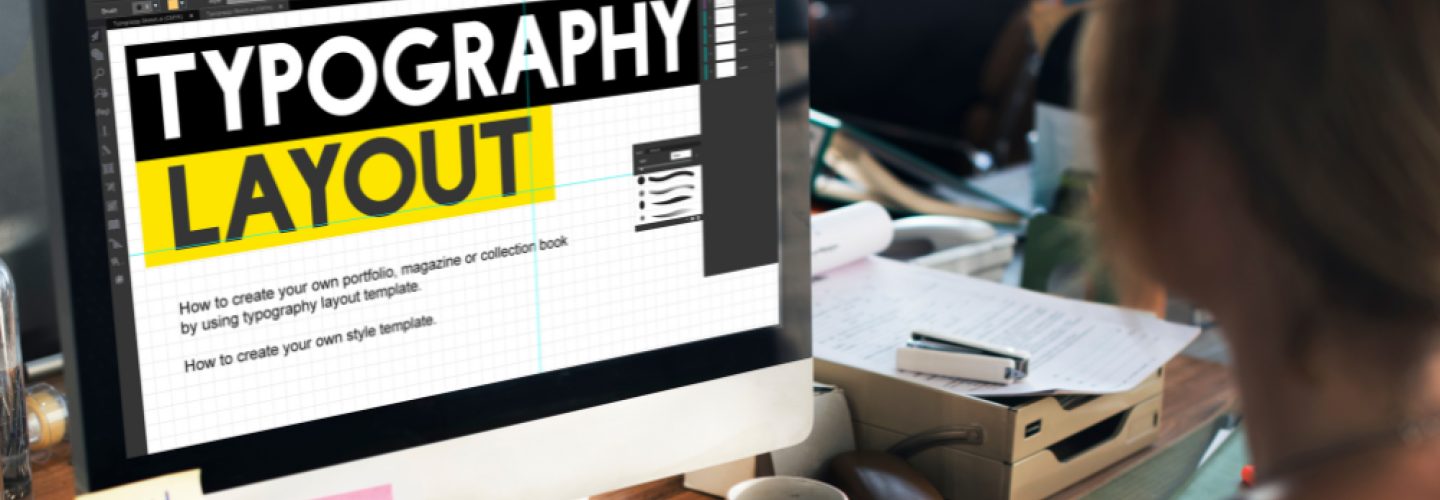
Como debes utilizar la tipografía para crear un impacto visual
La tipografía es, dentro del diseño gráfico y de lo relacionado con disciplinas como el motion design, uno de los elementos y recursos que puedes utilizar para impactar a quien vea el diseño o la grabación multimedia en la que se utilizan. Ya sean letras estáticas o en movimiento, la introducción de tipografía digital en el diseño, si se hace con las técnicas apropiadas, y eligiendo las mejores tipos con cuidado, puede causar un impacto visual notable. De hecho, es uno de los temas que tratan los estudiantes del Máster Online en Motion Graphics de ESDESIGN.
Comprendiendo las bases de las tipografías animadas
Antes de hablar de las bases de las tipografías animadas, o de cómo puedes animarlas, es conveniente aclarar a qué nos referimos cuando hablamos de tipografías animadas. Son, sencillamente, tipografías que se personalizan para crear una animación dinámica de las fuentes que las componen. Además, esta animación siempre va a ser única.
Las tipografías animadas se utilizan para añadir un toque personal e impactante a varios tipos de elementos digitales. Nos referimos a texto, mensajes y presentaciones. Generalmente, con el objetivo de incorporarlos a vídeos y animaciones de mayor envergadura.
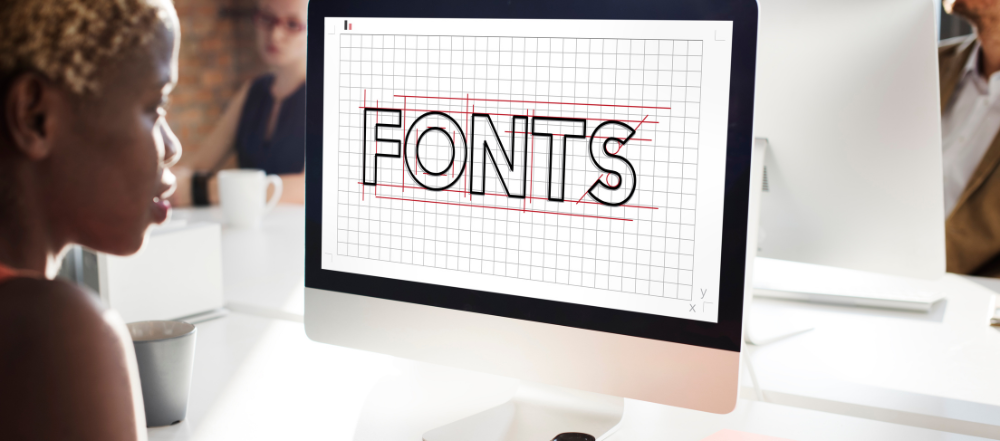
En cuanto a sus bases, una de las principales es que una tipografía animada se suele utilizar para resaltar lo que dicen las palabras o expresiones que se animan. También, para amplificar sus mensajes. En definitiva: se trata de un elemento que no solo provoca impacto; también, atrae la atención de quien lo ve.
Asimismo, se utiliza para mejorar la comunicación y para lanzar un mensaje en el momento y la situación elegidos por quien crea la animación. Por eso, no solo es necesario elegir con cuidado la animación de la que dotarás al texto; también es importante escoger el texto que animarás. De lo que digas en él dependerá, por ejemplo, el punto del vídeo en el que se insertará, o su movimiento.
Aprende a elegir la tipografía adecuada
Además de las bases que hemos señalado como las más importantes para la creación de tipografías animadas, hay otro elemento que tiene la misma relevancia que ellas -o incluso más-. Se trata de la tipografía que se utiliza en las animaciones. Su elección no es algo que tengas que dejar al azar, o escoger en base a tus gustos. Además de por su aspecto, debes tener en cuenta una serie de variables para elegir la que sea más adecuada en cada caso.
Entre lo que has de tener presente a la hora de seleccionarla están su geometría, es decir sus formas, y su peso. Ambos aspectos son importantes, porque no todos los tipos de letra permiten expresar el mismo mensaje. Así como tampoco lo hacen de la misma manera.
En cualquier caso, tienes que velar siempre para que las fuentes que selecciones puedan leerse con facilidad desde cualquier ángulo. También cuando el texto es de tamaño pequeño, o cuando se crea con letras grandes. Así conseguirás que, cuando formen parte de un texto animado, no haya complicaciones para entender el mensaje.
Técnicas y herramientas
La creación de tipografías animadas no tiene que hacerse de manera informal, ni con un programa que no sea el más adecuado para ello. Generalmente, la mejor opción para conseguirlo es un software de animación de propósito general con opciones específicas para la animación de tipografía. Entre ellos, destacar uno que es muy conocido en el mundo de la animación y el diseño gráfico: Adobe After Effects.
Este programa, sobre todo por la cantidad de opciones que ofrece para la generación de palabras y textos animados, está considerado como una de las herramientas más adecuadas para la animación de tipografía. Además, ofrece gran cantidad de plugins y herramientas centradas en poner palabras y trozos de texto en movimiento dentro de vídeos y animaciones. Eso sí, ten en cuenta que su manejo es algo complejo, por lo que puede costarte un poco dominar todas las funciones y opciones necesarias para animar texto.
Otra herramienta interesante para crear textos animados, así como vídeos y otro tipo de animaciones, es Renderforest. Se trata de un editor online, por lo que no es necesario instalarlo en el ordenador. Su curva de aprendizaje es mucho menor que la que presenta After Effects. Además, su coste es inferior, puesto que permite probarlo de manera gratuita, y solo necesitarás pagar por utilizar algunas de sus opciones. Por ejemplo, exportar las animaciones o vídeos creados con ella a HD.
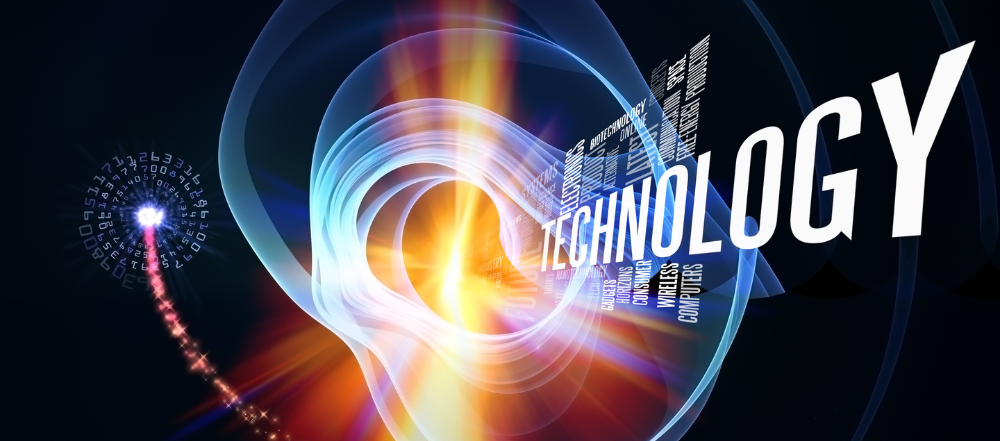
Si quieres facilitar aún más la creación de tipografías animadas, puedes utilizar plantillas. En internet encontrarás diversos sitios web donde podrás descargarlas. Tanto gratuitas, como Motion Array y Rocketstock; como de pago, que puedes encontrar en Envato Market.
Para animar tipografías, puedes usar diferentes técnicas. Por ejemplo, puedes utilizar ajustes de iluminación, profundidad de campo, perspectiva o escala de las letras. También puedes emplear recursos como deformaciones, o degradados de color. Si vas a incluir música en el vídeo en el que integres la animación del texto, cuida su sincronización con los movimientos de las letras. De esta manera, mejorará la comunicación del mensaje.
Como verás, las tipografías animadas van mucho más allá de una mera animación de letras en un vídeo. Tienen un propósito claro y, en muchos casos, su creación es mucho más relevante para la animación de lo que parece. Por eso, si quieres dedicarte, o te dedicas, a la animación y al motion graphics, ¡cuida siempre al máximo tus animaciones de tipografías!